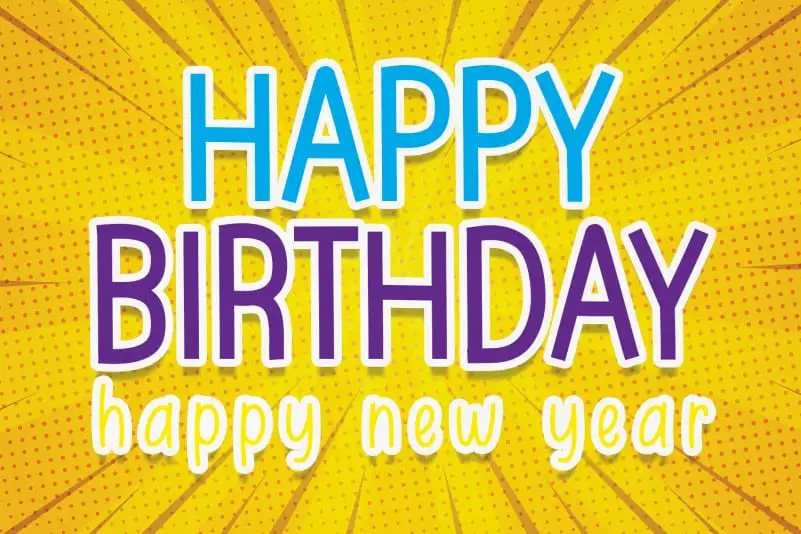
Aqui está uma breve descrição natural para a página de download da fonte “HAPPY BIRTHDAY Display Font” no formato solicitado: O HAPPIE BIRTHDAY Display Font é um conjunto criativo e visualmente atrativo projetado especialmente para momentos especiais como cumprimentos de aniversário. Feito pelo designer andikastudio, este recurso gráfico não apenas reforça o espírito festivo do dia 29 do mês (um número inspirado no nome da fonte), mas também oferece uma experiência visual memorável. Seja para cartões de aniversário, convites ou mensagens personalizadas, esta fonte é perfeita para dar um toque especial ao seu design. Com suas formas brilhantes e letras em destaque, ela transmite felicidade e emoção em cada letra que usa. Ideal tanto para eventos privados quanto públicos, este é o complemento ideal para qualquer projeto gráfico onde você quer destacar a importância da data de aniversário. Há algo tão especial nessa fonte quanto o próprio dia 29 do mês! Descubra por si mesmo como ela pode transformar seus designs.